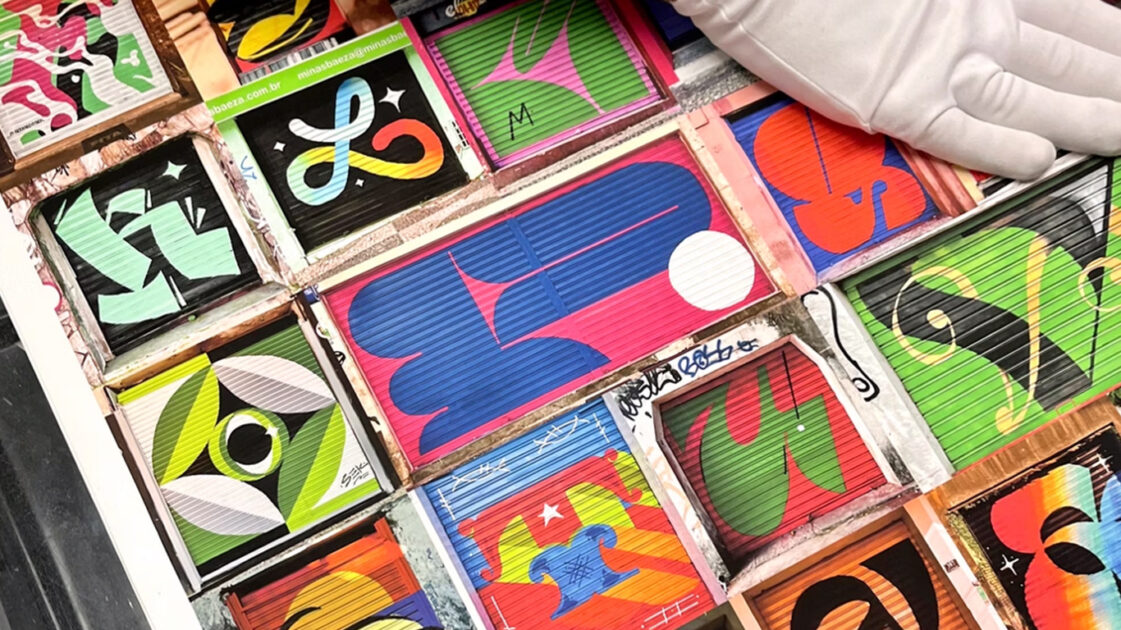
O designer gráfico, grafiteiro e letrista mineiro Bernardo Sek foi um dos vencedores do Type Directors Club (TDC), uma das premiações mais importantes do mundo no campo da tipografia em todo o mundo.
O trabalho Letraço, que consiste na concepção de um alfabeto sobre portas de aço, recebeu o Certificate of Typographic Excellence na categoria Lettering, concedido por um júri internacional.
A obra é uma pesquisa visual que explora a tipografia experimental e sua conexão com o grafite, criando um alfabeto completo a partir de portas de aço do comércio de Belo Horizonte. O trabalho combina princípios do design gráfico, como contraste e alinhamento, com a essência do grafite urbano. Para os viciados em bienais, talvez já tenha visto o “Letraço” como destaque nacional na 14ª Bienal Brasileira de Design.
Em tempo: além de Sek, o projeto envolve a artista e designer Tainá Evaristo atua como colaboradora, contribuindo para sua mediação poética e interpretação crítica.
A estudante Tainá Evaristo Felizardo, do 9º período do curso de Design da UFMG, integrou um dos projetos vencedores da 71ª edição do Type Directors Club Awards (TDC), um dos principais prêmios de tipografia do mundo.
A obra foi exibida neste mês, em Nova York, durante o festival The One Club for Creativity, e passou a integrar o anuário The World’s Best Typography. A exposição também circulará por museus e escolas em países como Japão, França, Alemanha e Coreia do Sul.
Contribuições
Letraço – uma porta fechada é uma tela em branco [veja galeria de fotos no site do DCA] é um projeto com concepção e direção criativa do designer Bernardo Sek. A concepção de arte em portas de aço, tem a intenção de “revelar histórias da cidade, do som das ruas e da poesia cotidiana”, informou Tainá Evaristo.
A estudante da UFMG contribuiu para a construção conceitual, organização visual, curadoria de conteúdo e preparação de material para inscrições e exposições. “Também atuei na tradução editorial e institucional do projeto, além da montagem da exposição na Galeria Vessie, em Belo Horizonte”, relata.
Sobre a participação no concurso, a estudante considerou especialmente gratificante o contato com projetos que envolvem variações tipográficas no idioma hindi, aplicações em espaço público e outros projetos universitários. “Estive com mulheres que atuam na tipografia e designers que admiro, como Carlos Oliveiras Colom e Jason Carne”, acrescenta. Para Tainá, a experiência reforçou a ideia de que “podemos disputar com grandes marcas criando projetos autorais dentro da universidade”.